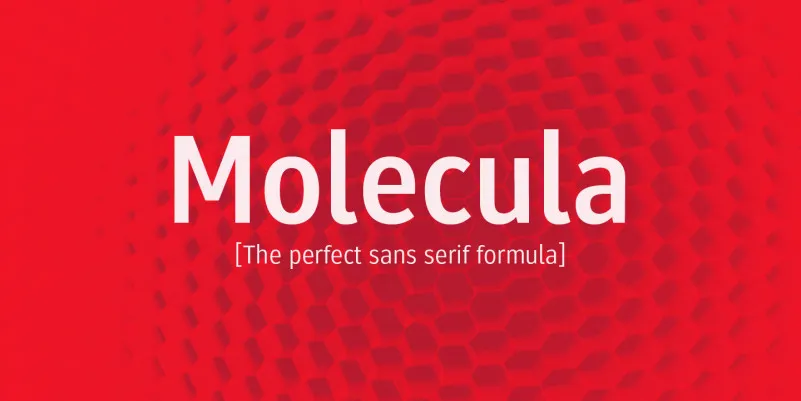
A fonte Molecula é uma grotesca sans serif com proporções ligeiramente afiadas e elementos humanistas-grotescas. Esta família oferece nove pesos, desde fino até grosso, cada um acompanhado de uma itálica. O conjunto de caracteres está robusto, abrangendo extensões do latim. Todas as fontes contêm recursos OpenType úteis, incluindo gílias alternativas, frações, números alinhados, minúsculas grandes e sublinhadas e sobrescritas. Uma vez que você está procurando por um estilo fresco e moderno para seus projetos digitais, a Molecula oferece exatamente isso: linhas estilizadas e fluidas que certamente irão destacar seu texto. Seja em uma página de site ou em um documento profissional, essa fonte proporcionará o toque distintivo que você precisa para dar vida à sua mensagem. Com Molecula, a escolha do tipo nunca foi tão simples e versátil quanto agora.
Designer: Northeast Type Foundry